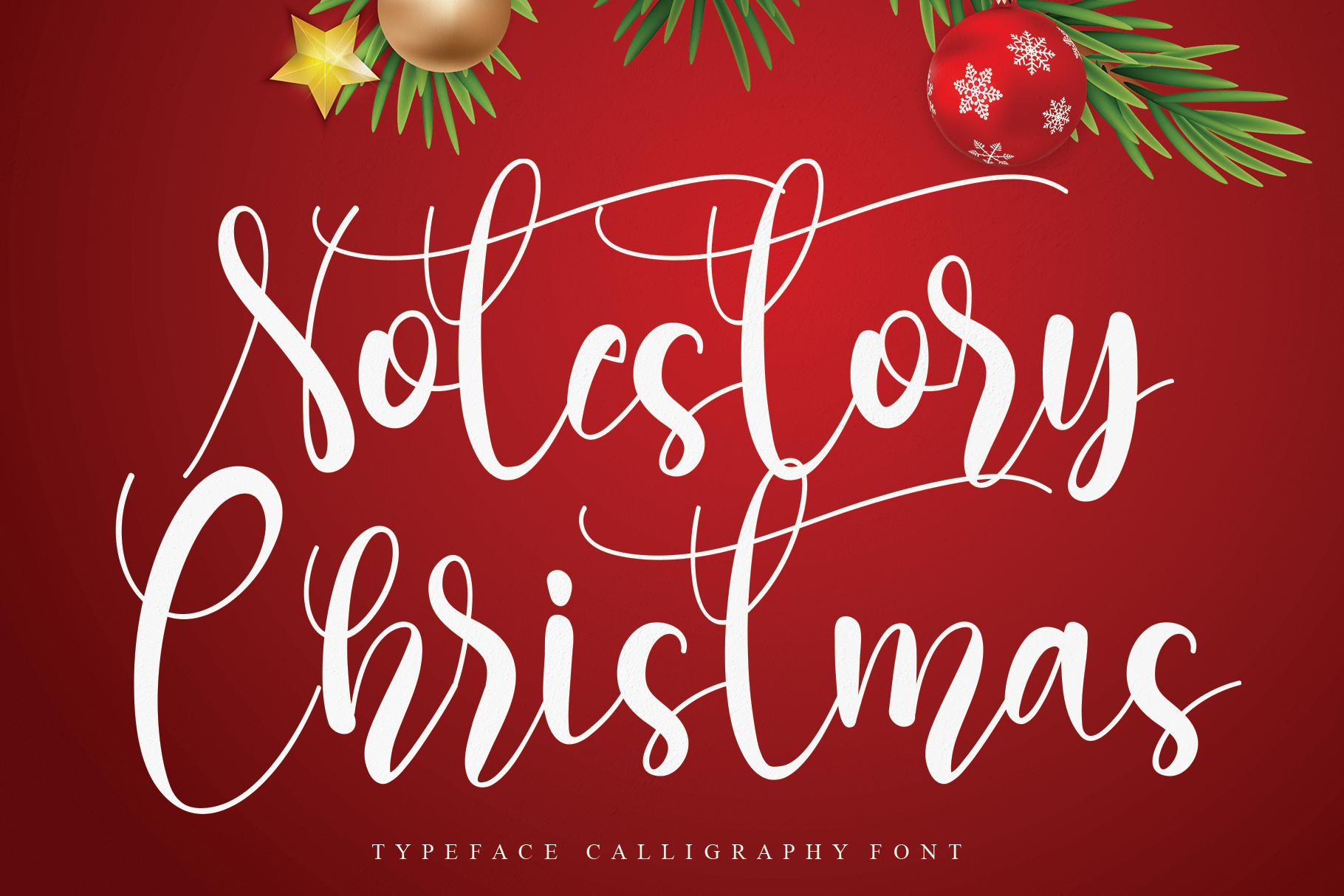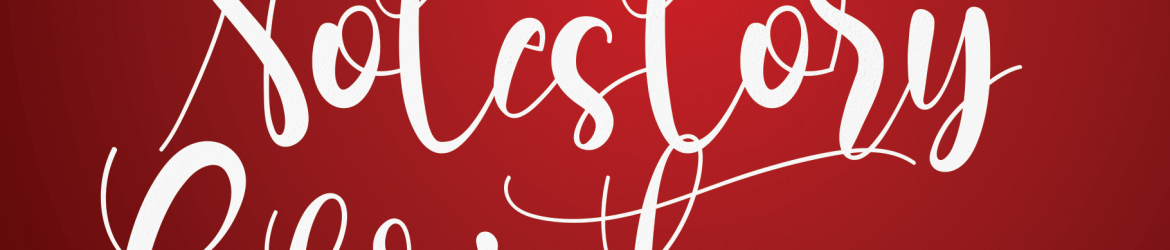
A Notestory Christmas Font é uma deliciosa mão-dura para aqueles que buscam adicionar um toque de charme a seus trabalhos digitais. Esta elegante fonte é perfeita para quem deseja dar uma pitada especial e criativa aos eventos natalinos ou mesmo em qualquer projeto que necessite de gravações delicadas. Com seu estilo inovador, este ‘handwritten’ está disponível para uso em uma ampla gama de aplicações incluindo: embalagens de produtos, cartões de convite, logotipos para mídias sociais e até mesmo sobras de foto. A Notestory Christmas Font é uma excelente adição aos recursos gráficos que tanto contribuem para enriquecer qualquer projeto de design digital, tornando-o ainda mais único e envolvente.